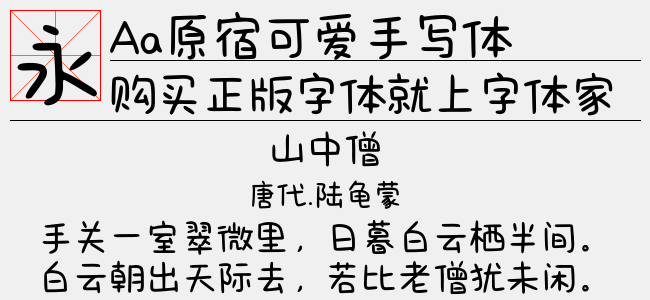
Aa原宿可爱手写体
字体作者:Aa字库
字体名称:Aa原宿可爱手写体
字体家族:Aa字库
书体类型:手写/印刷体
Aa原宿可爱手写体
Aa原宿可爱手写体是一款不错的艺术字体,由Aa字库出品,字体笔触纤细,书写流畅,字形端正,具有很好的视觉感,适合应用于艺术设计、平面宣传设计、网页设计,书法字帖等领域,需要的朋友可以前来本站下载。